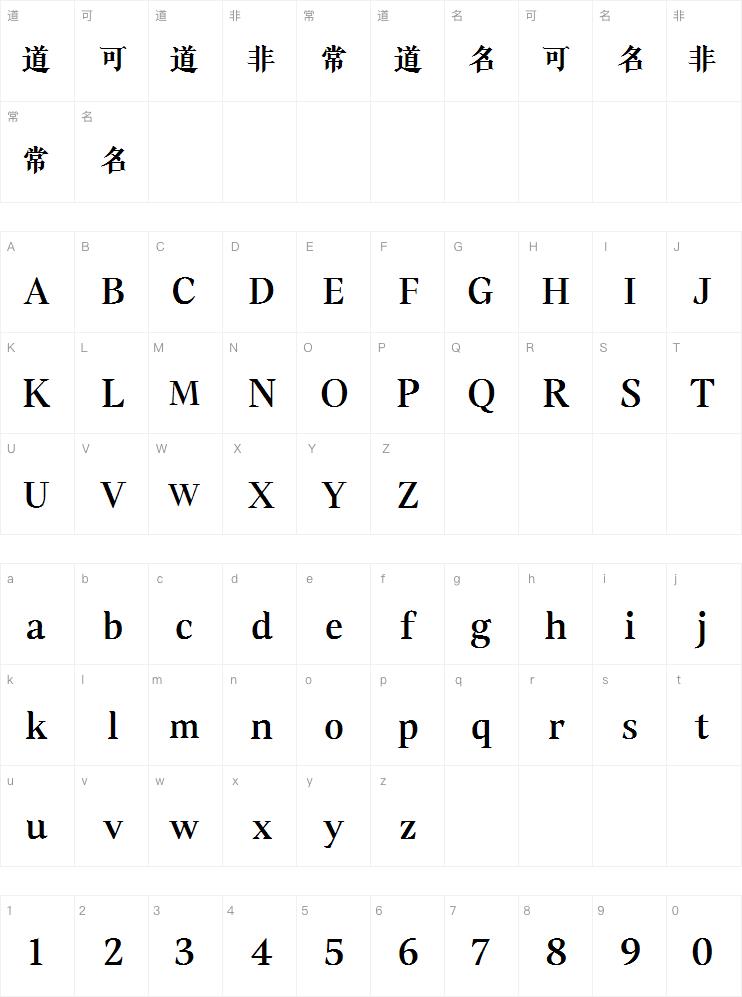
山海汲古明刻 简繁
山海汲古明刻 简繁,是一款全新的字体,包含简繁汉字9414个,符号200+个,是一款国风复古刻本字体。字形秉承中国古代古籍善本之字形特性,版刻刀法剔透,字形方正,端庄严谨,古朴大方,起落顿笔有棱角。在饱有笔墨之意的同时,又突显刀刻之锋美,笔刀结合刚柔并济。在秉承笔形间创新,结合当代设计视觉环境,融入现代审美,适用场景更多元,笔画造型清晰锐利,删繁取简,笔锋凌厉,速度感强,粗细对比强烈,重现刀刻古韵之美。
山海汲古明刻 简繁